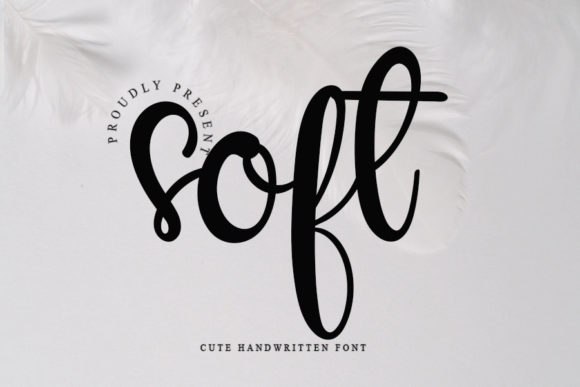
Soft
Soft : la police manuscrite qui allie élégance classique et modernité
Vous cherchez une police Soft capable de sublimer vos projets graphiques tout en conservant une touche d’authenticité ? Ne cherchez plus. Soft est une police manuscrite stylisée, inspirée d’une calligraphie classique intemporelle, mais repensée pour répondre aux exigences du design contemporain. Sa forme impeccable et son atmosphère actuelle en font le choix idéal pour quiconque souhaite allier raffinement et modernité dans ses créations.
Grâce à son style élégant et à sa lisibilité remarquable, Soft s’intègre parfaitement dans une multitude de contextes : branding, affiches, sites web, invitations, packaging ou encore présentations PowerPoint. Son allure sophistiquée capte immédiatement l’attention et donne à chaque texte une personnalité unique.
Pourquoi choisir la police Soft ?
- Design intemporel : inspirée d’une calligraphie classique, elle conserve une élégance qui ne se démode jamais.
- Aspect contemporain : les traits épurés et la structure équilibrée offrent une touche moderne adaptée aux tendances actuelles.
- Polyvalence : parfait pour les logos, les titres, les citations, les menus de restaurant ou les cartes de vœux.
- Lisibilité optimale : même en petite taille, les formes restent claires et nettes, garantissant une lecture fluide.
Comment exploiter au mieux Soft dans vos projets ?
- Utilisez Soft pour les titres et en-têtes afin d’attirer l’attention des visiteurs et des moteurs de recherche.
- Combinez-la avec une police sans‑serif neutre (ex. : Open Sans, Lato) pour le corps du texte afin d’assurer une lecture confortable.
- Profitez de ses caractères gras ou italique pour créer une hiérarchie visuelle claire et améliorer le temps de rétention des utilisateurs.
En résumé, la police Soft représente le parfait compromis entre tradition et innovation. Que vous soyez designer, marketeur ou créateur de contenu, elle vous aidera à créer des visuels mémorables tout en renforçant votre visibilité en ligne grâce à une optimisation SEO ciblée.